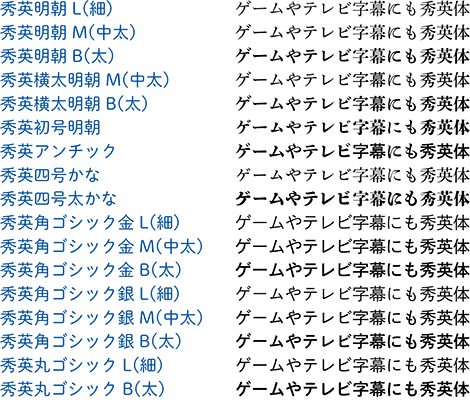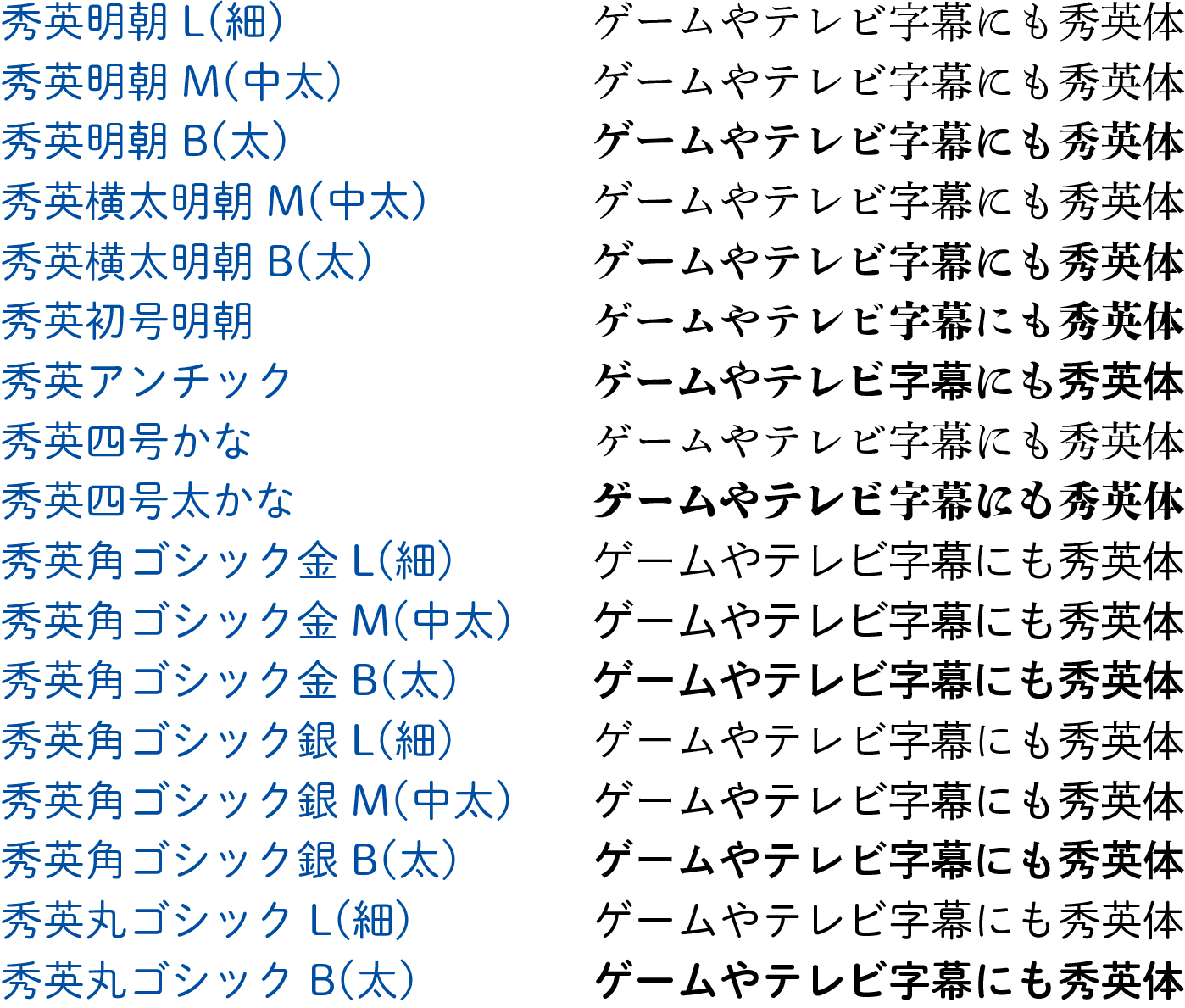
フォントワークス LETSでの『秀英体』提供が始まりました!
提供書体:
・秀英明朝L/M/B
・秀英初号明朝
・秀英横太明朝M/B
・秀英アンチック
・秀英四号かな
・秀英四号太かな
・秀英角ゴシック金L/M/B
・秀英角ゴシック銀L/M/B
・秀英丸ゴシックL/B
DNPは、オリジナル書体「秀英体」の17書体をフォントワークス株式会社にライセンス提供し、フォントワークスは同社の年間定額制フォントサービス「LETS」のラインナップとして、2017年7月11日に秀英体の提供を開始しました。
「LETS」の利用者は、各種出版物や電子書籍、Webサイトや映像・ゲームなどのコンテンツ、ポスターや商品パッケージ、DMなどの製品および販促物などに、美しく読みやすいと定評のある「秀英体」17書体を活用することができます。